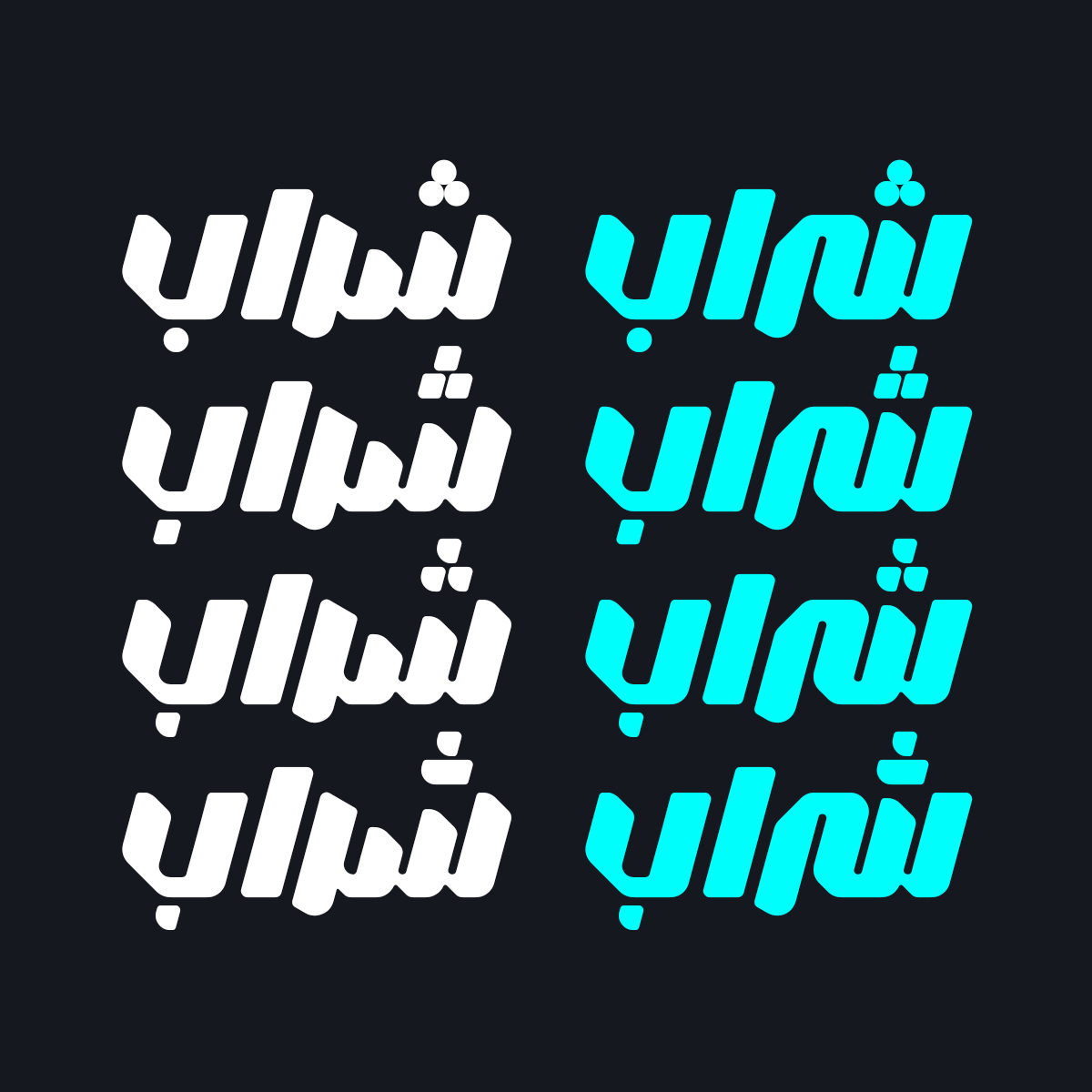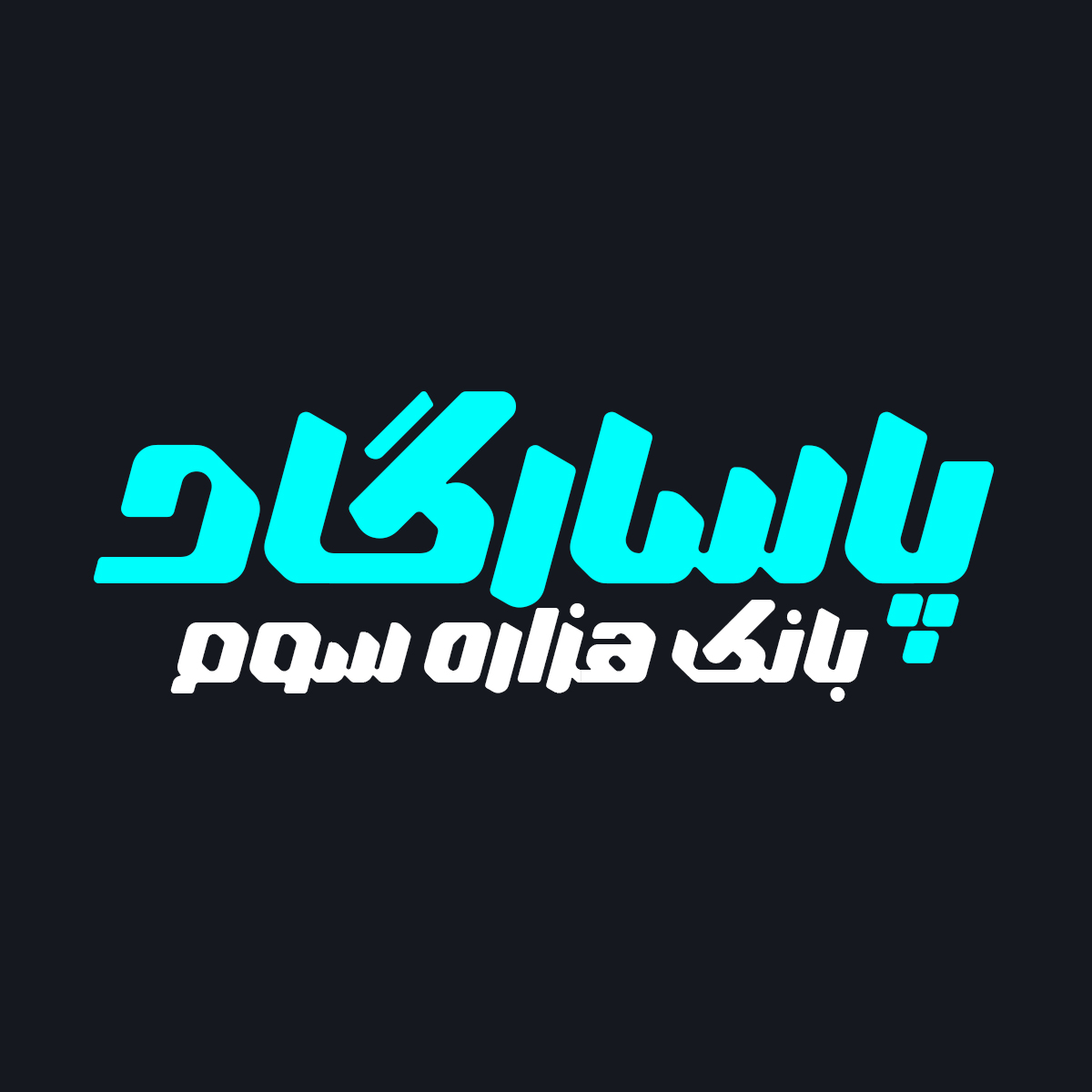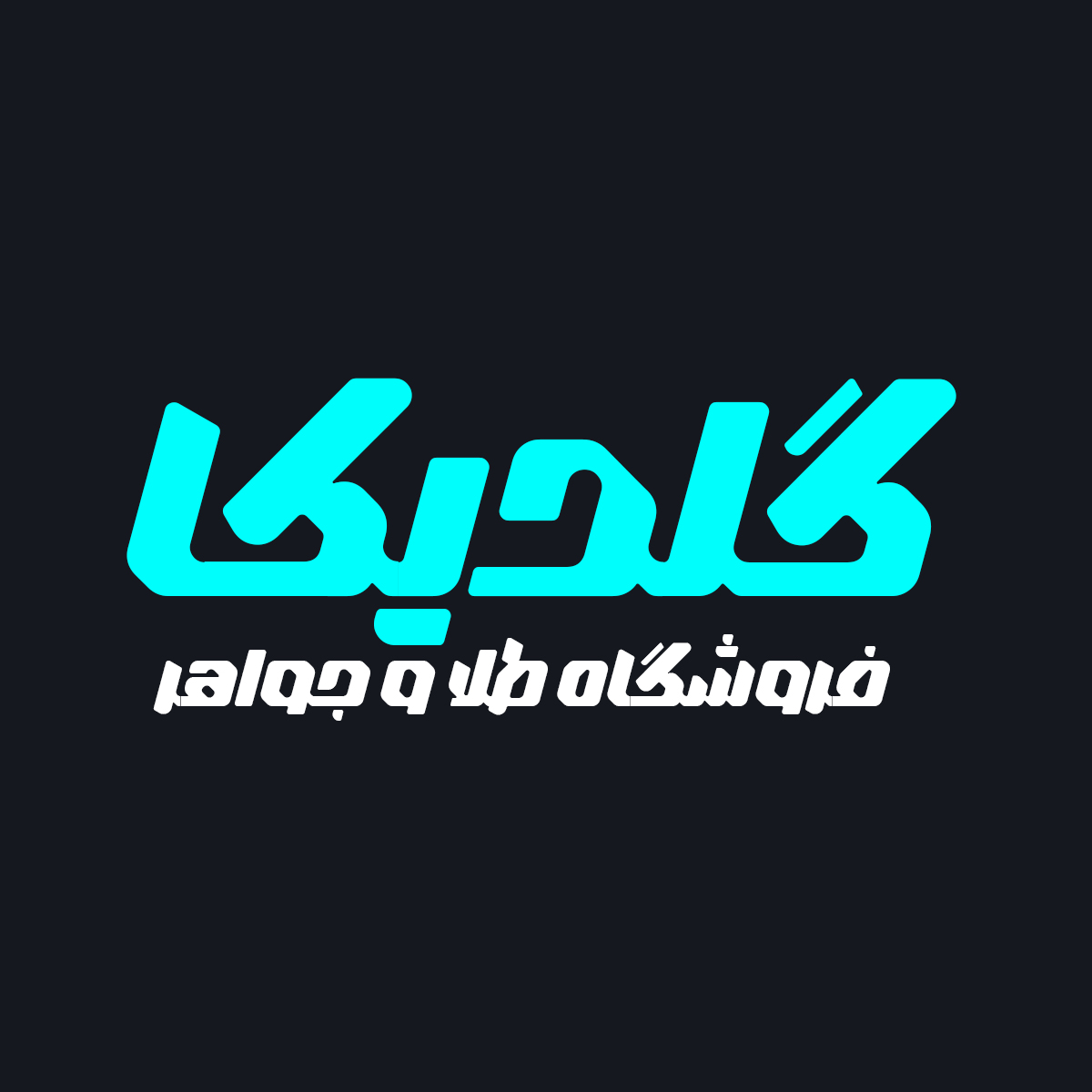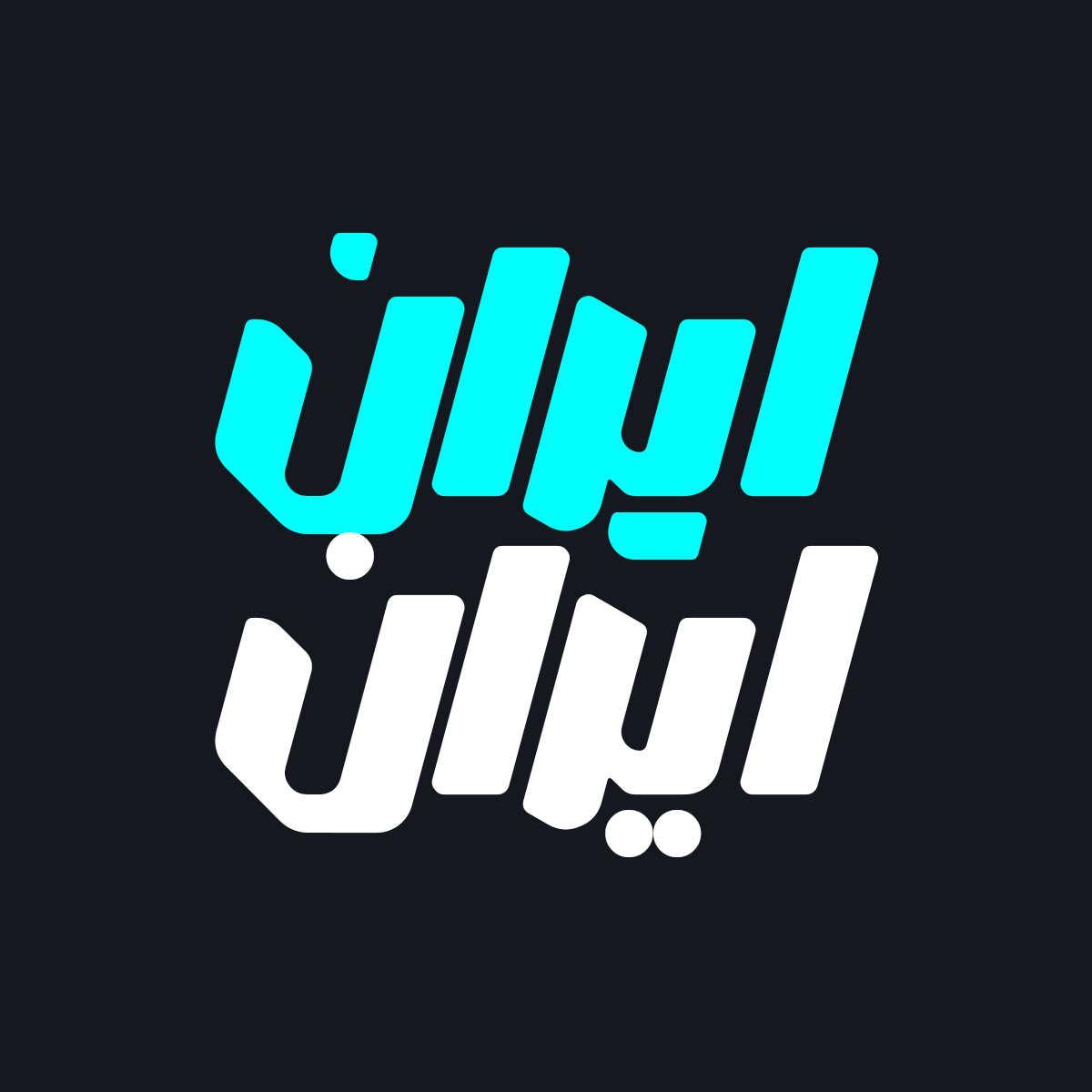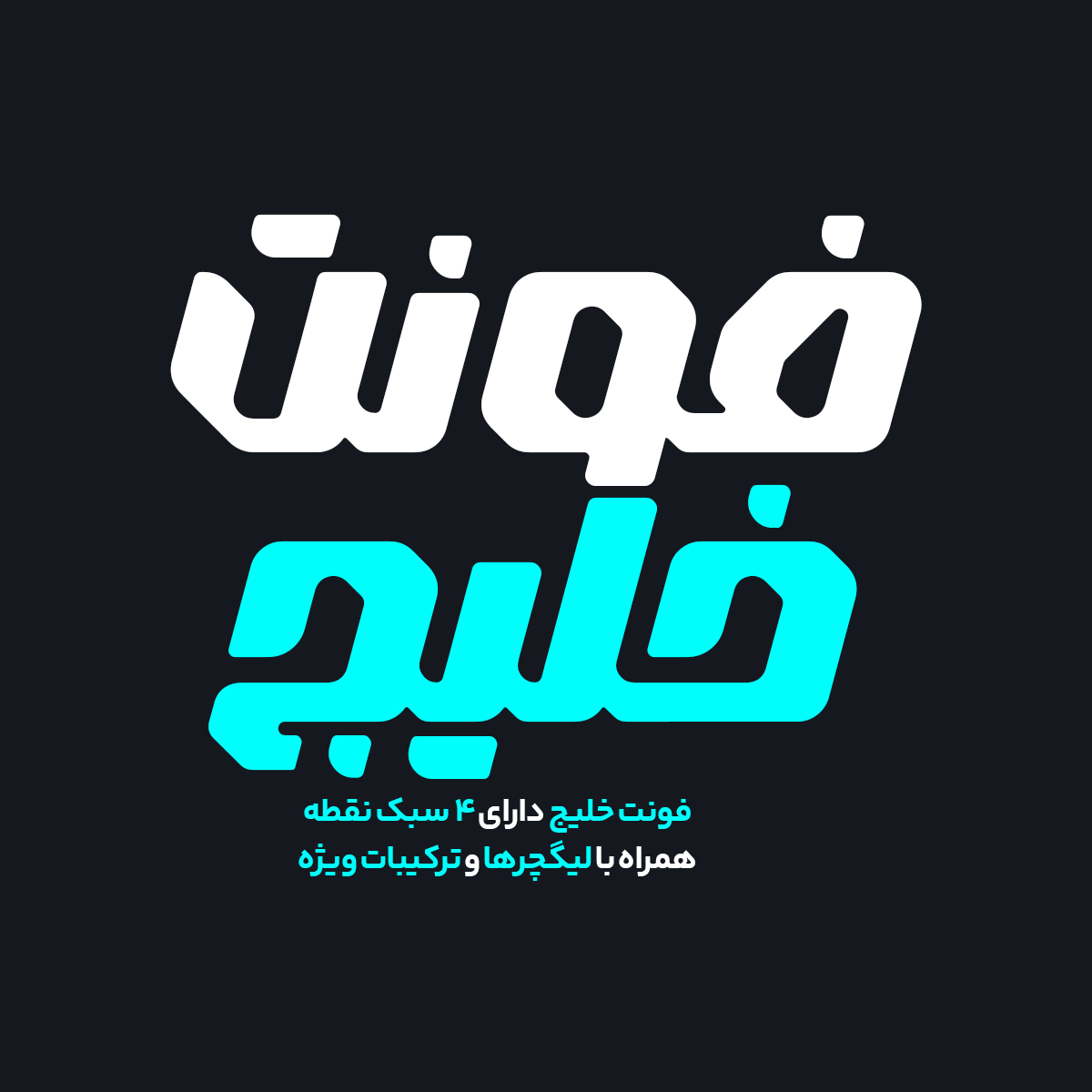
فونت فارسی خلیج Khalij Font
فونت خلیج + نسخه جدید
فونت فارسی خلیج یک فونت بر مبنای هندسی و خاص که دارای چهار سبک نقطه و همراه با لیگچرها و ترکیبات ویژه می باشد و به طراحان گرافیک امکان خلق طرح های زیبا و حرفه ای به سادگی تایپ می دهد. فونت خلیج شامل چهار نسخه و دارای منحنی های زیبا، دوستانه، مدرن و خوانا می باشد.
این فونت با ساختار حروف منحصر به فرد خود مناسب استفاده در لوگوهای نوشتاری می باشد. همچنین از این فونت در طراحی تابلوهای چلنیوم هم به دلیل ساختار منحصر به فردش می توانید استفاده کنید. در ادامه برای شما نمونه تایپ های این محصول حرفه ای رو آماده کرده ایم که میتوانید مشاهده کنید.
در فرایند بازطراحی فونت فارسی خلیج چه کارهایی انجام شد؟
- اضافه شدن یک سبک نقطه دیگر به فونت
- بازبینی و تنظیم فاصله گذاری بین حروف
کاربرد فونت فارسی خلیج
پیشنمایش و نمونه تایپ های فونت خلیج